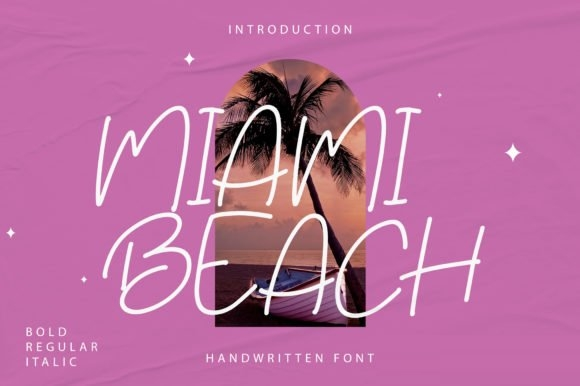
[Creativefabrica] Miami Beach Font (2021)
Название: Miami Beach Font (2021)
Miami Beach - это классный, простой и неформальный рукописный шрифт.
Его можно использовать для различных целей, таких как логотипы, свадебные приглашения, заголовки, футболки, бланки, вывески, этикетки, новости, плакаты, значки и многое другое.